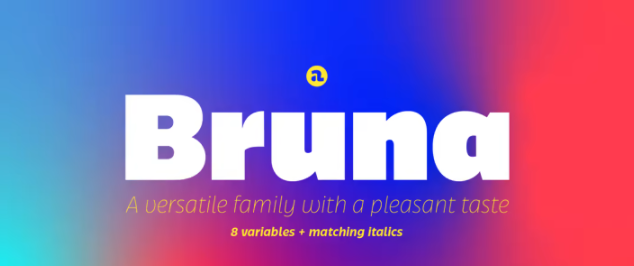
Bruna - полезное семейство шрифтов для текста и отображения. Универсальное семейство с приятным вкусом.
Мы разработали семейство из 16 шрифтов с более чем 900 различными глифами, такими как малые прописные, высшие, низшие, дробные, табличные, цифры старого стиля и подкладки, математические, цифры и т.д. Позволяет составлять сложные редакционные композиции.
Его открытые счетчики и большая высота x дают ему отличную производительность при малых размерах. С другой стороны, изогнутые диагонали, большая ширина и мягкие формы придают ему дружелюбный, но функциональный характер для широкого спектра сообщений и тонов голоса.
Мы рекомендуем четыре наиболее экстремальных варианта веса (тонкий, сверхлегкий, черный и тяжелый) для больших размеров от 18 пунктов и пять промежуточных (легкий, обычный, средний, полужирный и полужирный) для малых размеров от 6 пунктов.